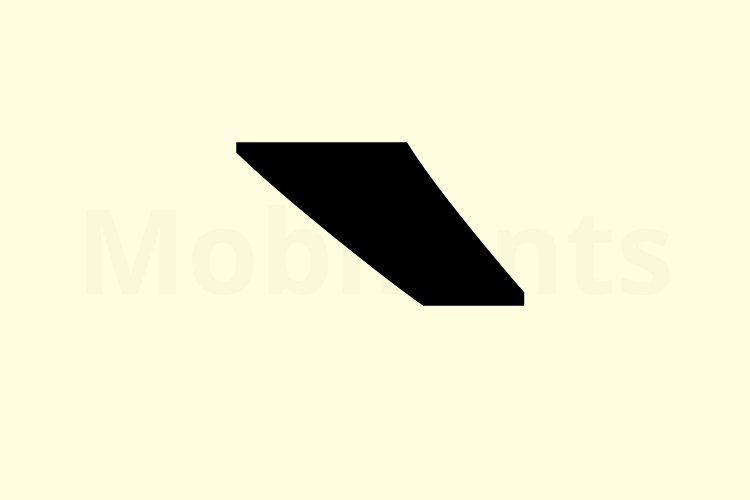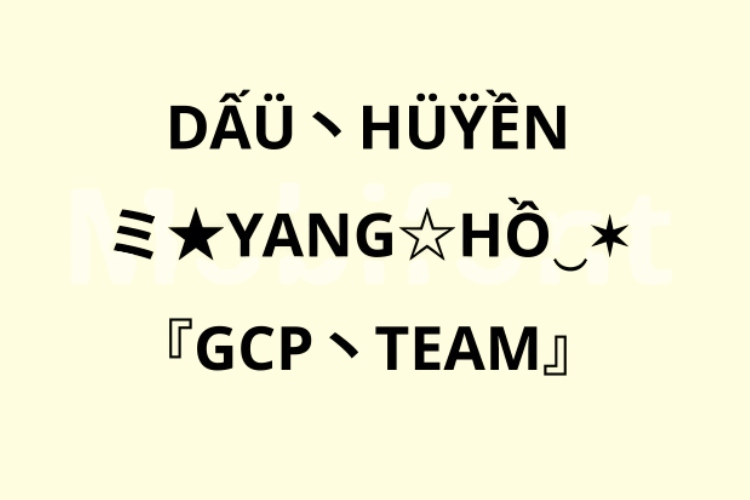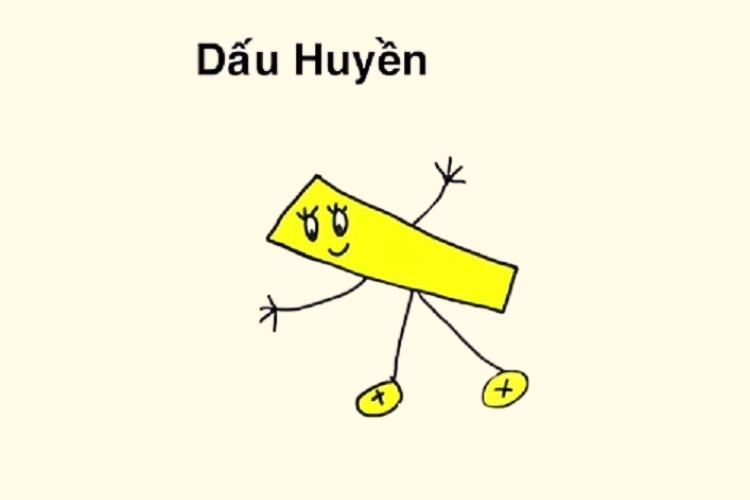
Bộ sưu tập 100+ kí tự dấu huyền sáng tạo gây sốt mạng xã hội
Dấu huyền không đơn giản là ký hiệu ngữ âm mà còn là một điểm nhấn thẩm mỹ khi sử dụng trong tên game, bài viết mạng xã hội hay kí tự nghệ thuật. Mobifonts mang đến kho kí tự dấu huyền sáng tạo, giúp bạn cá nhân hóa nội dung và tạo dấu ấn riêng biệt.
Dấu huyền biểu thị thanh huyền - một trong sáu thanh điệu cơ bản trong tiếng Việt. Khi được đặt lên một nguyên âm, dấu huyền làm thay đổi âm điệu của từ, giúp câu văn trở nên dễ hiểu và truyền đạt đúng sắc thái cảm xúc. Đây là kí tự dấu có tần suất sử dụng rất cao trong cả văn viết lẫn lời nói hàng ngày.
Ứng dụng thực tế của kí tự dấu huyền:
Website của chúng tôi đã tổng hợp nhiều mẫu kí tự dấu huyền phổ biến, dễ sao chép, phù hợp dùng cho mọi nền tảng từ Facebook, Zalo, TikTok đến các tựa game như Liên Quân, Free Fire.
Các kí tự trên có thể kết hợp với chữ cái để tạo thành tên nhân vật game, đoạn mô tả hoặc văn bản mang đậm chất cá nhân và rất ít trùng lặp.
Việc kết hợp kí tự dấu huyền với chữ thường hoặc biểu tượng giúp người dùng tạo dấu ấn riêng biệt trong game hay profile mạng xã hội. Đây là xu hướng được giới trẻ đặc biệt yêu thích vì dễ sáng tạo và gây ấn tượng mạnh.
Ví dụ:
Chỉ cần thay dấu bình thường bằng kí tự dấu huyền là bạn đã có ngay một tên hiển thị cực độc lạ.
Muốn tên hiển thị của bạn trở nên cuốn hút hơn? Những kí tự dấu huyền dưới đây chính là lựa chọn hoàn hảo để tạo điểm nhấn không trùng lặp.
Từ kí tự dấu mềm mại đến những cách viết “xịn sò” đầy sáng tạo, tất cả đã được tổng hợp sẵn cho bạn:
Bộ sưu tập dưới đây sẽ mang đến cho bạn những mẫu kí tự đặc biệt dấu huyền ngẫu nhiên, phá cách và đầy ấn tượng, đảm bảo “không đụng hàng”.
Sự pha trộn của các ký hiệu đặc biệt tạo nên các mẫu kí tự dấu huyền xáo trộn có một không hai. Phù hợp với người thích sự khác biệt, muốn phá vỡ mọi khuôn mẫu.
Từ dạng viết tay, in đậm, chữ vuông cho đến kiểu Greek hay Latin hoá, các mẫu bên dưới là sự tổng hợp đa dạng nhất của kí tự dấu huyền theo mọi phong cách.
Cuối cùng, để bạn hiểu rõ hơn về cách sử dụng dấu huyền mà không gặp rắc rối, đây là phần giải đáp những thắc mắc thường gặp nhất.
Thông thường kí tự dấu huyền dạng chuẩn Unicode sẽ hiển thị tốt trên mọi nền tảng. Tuy nhiên, nếu kết hợp quá nhiều kí tự lạ, có thể gây lỗi trên một số thiết bị đời cũ. Tốt nhất là kiểm tra trước khi lưu tên hoặc đăng nội dung.
Hoàn toàn được. Hầu hết các trò chơi như Liên Quân Mobile, Free Fire, Play Together, hay PUBG Mobile đều hỗ trợ kí tự Unicode, trong đó có cả kí tự dấu huyền. Tuy nhiên, một số game có giới hạn về độ dài tên hoặc không cho phép dấu chồng ký tự, nên bạn nên kiểm tra trước khi lưu tên chính thức.
Dĩ nhiên là được. Rất nhiều người dùng đã thử kết hợp dấu huyền với kí tự cute, icon hoa lá hoặc biểu tượng đặc biệt như:
Những tổ hợp này không chỉ tạo điểm nhấn mà còn giúp cá nhân hóa nội dung hiệu quả hơn.